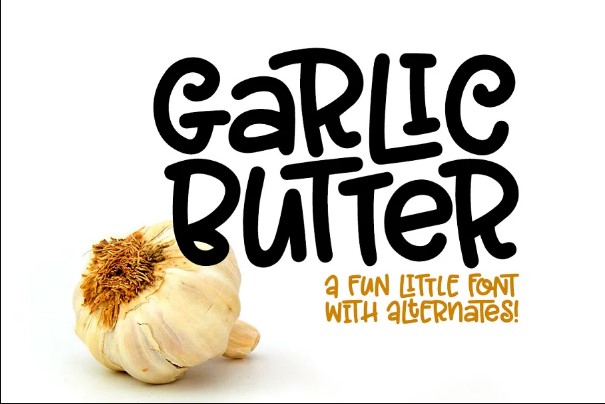
Creativemarket Garlic Butter Font
[Creativemarket] Garlic Butter Font
Оно гладкое, милое, весёлое и очень вкусное: это чесночное масло!
Смешанный шрифт с большим количеством комбинаций.
Чесночное масло - это пара шрифтов, идеально подходящих для всех Ваших забавных рисунков. Основной файл шрифта поставляется с обычными символами (A-Z, a-z, 0-9 и тоннами пунктуации), а также с более чем 300 акцентированными символами для поддержки большинства латиноамериканских языков. Кроме того, он поставляется с более чем 150 лигатурами и альтернативными буквами!
Вы также получите файл чесночных капсул, полный вихрей, слешей, иконок, головок со стрелками и хвостов, лозунгов и других декоративных элементов. Все они были созданы одной кистью, и их размеры совпадают с размерами букв Чесночного масла, так что можете быть уверены, что они отлично подойдут друг другу!